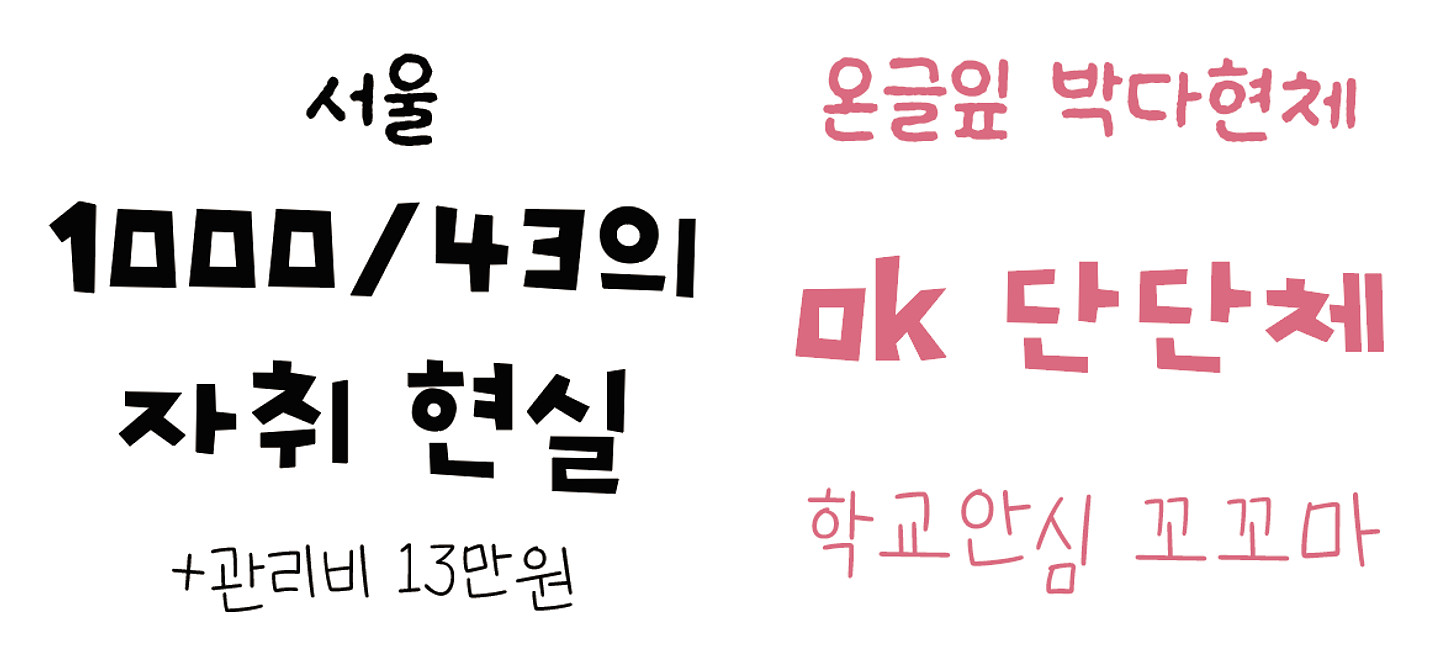
서울 - 온글잎 박다현체 ( https://www.ownglyph.com/trial/11ebf7f8-0997-4f03-a393-0959a07286aa ) / 1000/43의 자취 현실 - ok 단단체 ( https://www.okticon.com/freefont/?q=YToxOntzOjEyOiJrZXl3b3JkX3R5cGUiO3M6MzoiYWxsIjt9&bmode=view&idx=169969648&t=board ) /, +관리비 13만원 - 학교안심 꼬꼬마체입니다! ( https://copyright.keris.or.kr/wft/fntDwnldView?fntGrpId=GFT202312110000000000004 )
제발 도와주세요ㅠㅠ ㅠㅠ 꼭 이게 아니더라도 비슷한 느낌의 폰트나 단어가 있을까요....? 손글씨라기엔 요즘 외국에서 사용하는 폰트같은게 다른 가게에서도 비슥한 폰트를 보았어서요 ㅜㅠ